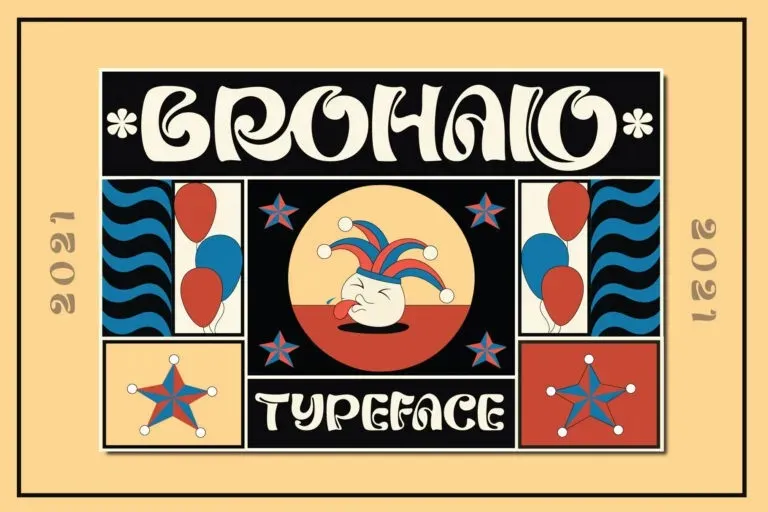
Brohalo Font – Download Grátis
A Brohalo Font é uma fonte display que surgiu do talento visionário do designer alit design. Inspirada nos estilos vintage dos anos 70, essa fonte tem um visual agressivo e retro, com linhas sólidas que remetem aos designs icônicos da época. Ela traz ao mundo uma sensação descontraída, divertida e clássica sem perder em beleza ou singularidade. Perfeita para aplicações visuais, como títulos de slide ou design gráfico de arte, a Brohalo é fácil de recordar e transformará seu projeto num ícone distintivo. Seja você um estilista ou uma marca que busca modernidade e personalidade, essa fonte será sua escolha perfeita.